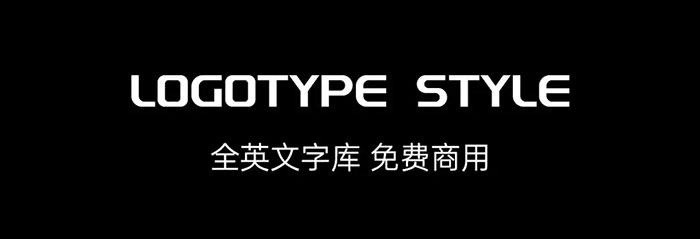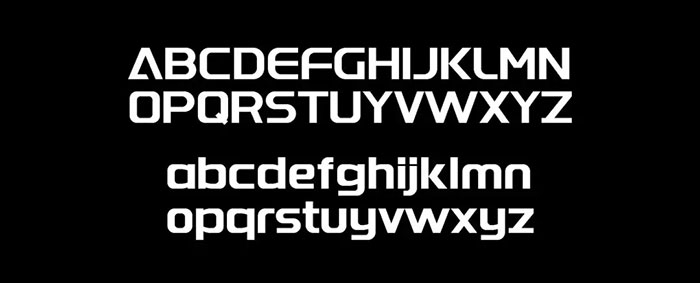
這是一套全英文字庫,適用於標題、LOGO設計等場合使用,所以只做了52個英文10個數字和幾個標點。這套字巧妙之處在於,如果你的公司需要設計LOGO,但你不會做LOGO設計,你可以把字打出來,調個間距,調個顏色,國際化立馬飆升!無論是互聯網公司,還是服裝品牌,還是玩具公司,還是食品公司,還是大型企業等等,都是很適合的!